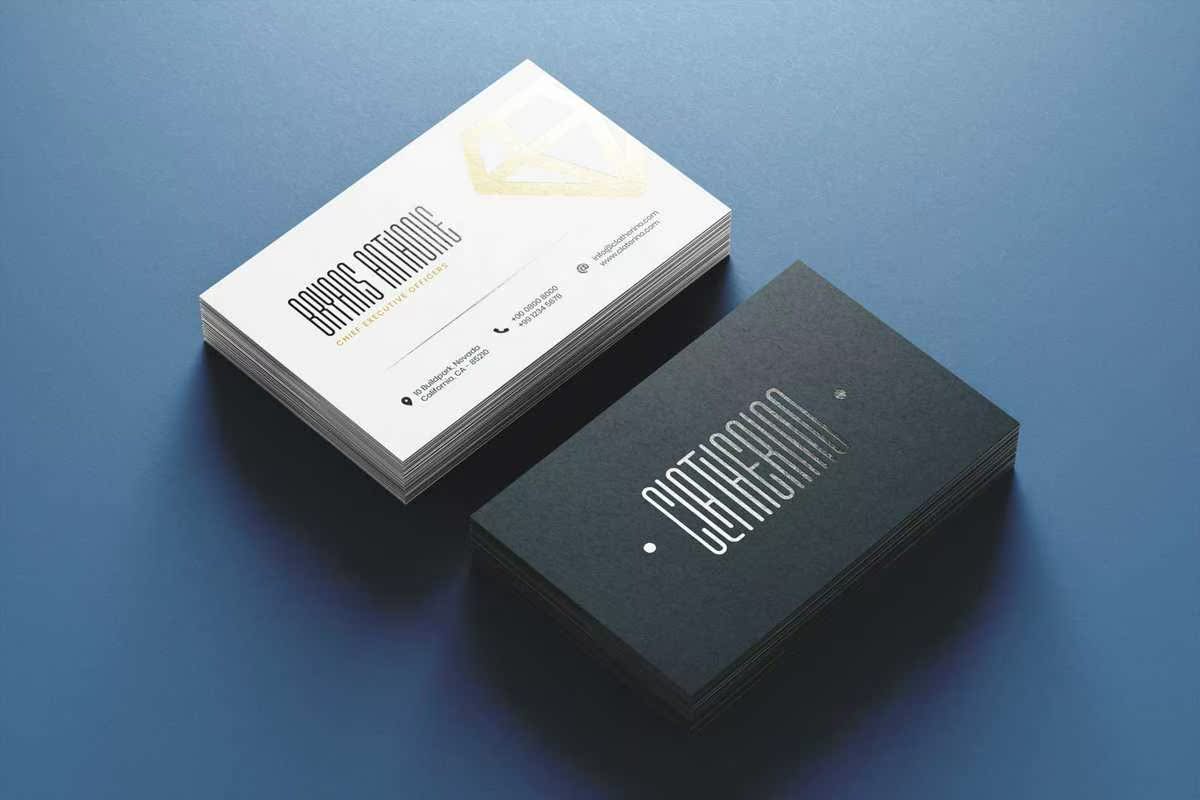
Marbelly是一款简单而优雅的Sanserifont,具有奢华的风格,可用于06风格:浓缩、浓缩、浓缩双线、粗体浓缩、粗体浓缩和粗体浓缩双线,包括交替、连字和多语言支持。Marbelly是一款简单而优雅的Sanserifont,具有奢华的风格,可用于06风格:浓缩,CongregateDiTalic、CongregateDoutLine、BoldCongregateDiTalic和BoldCongregateDoutLine包括可选、连字和多语言支持。